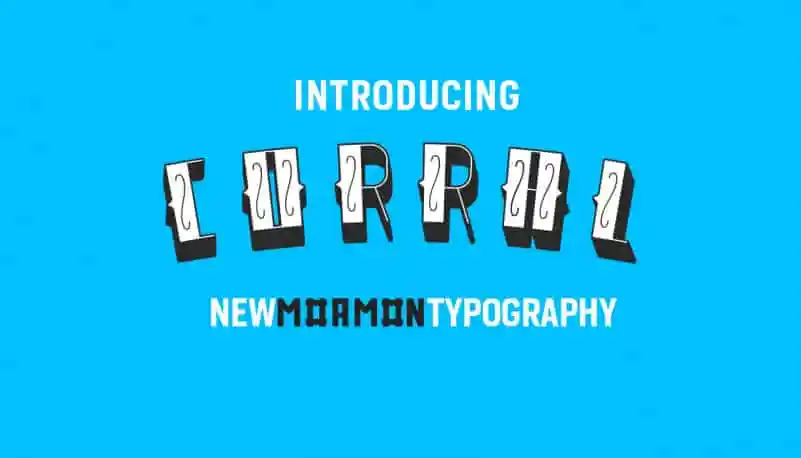
A Corral Display Font é uma elegante tipografia projetada para estilos western, inspirada nas histórias e costumes de cowboys e vaqueros. Ideal tanto para logos quanto para badges ou marcos em lojas, ela também se destaca perfeitamente para headlines, sub-headlines e até mesmo textos do corpo. Se você busca um tipo que reflita estilo antigo, vintage ou arte pop retro, esta fonte é uma ótima escolha. Idealmente recomendada para ambientes com temas western, a Corral Display Font adiciona uma atmosfera única aos projetos de design. Com sua personalidade assertiva e seu apelo visual envolvente, ela se sobressai como um recurso versátil para designers em busca de uma fonte que expressa força e estilo.